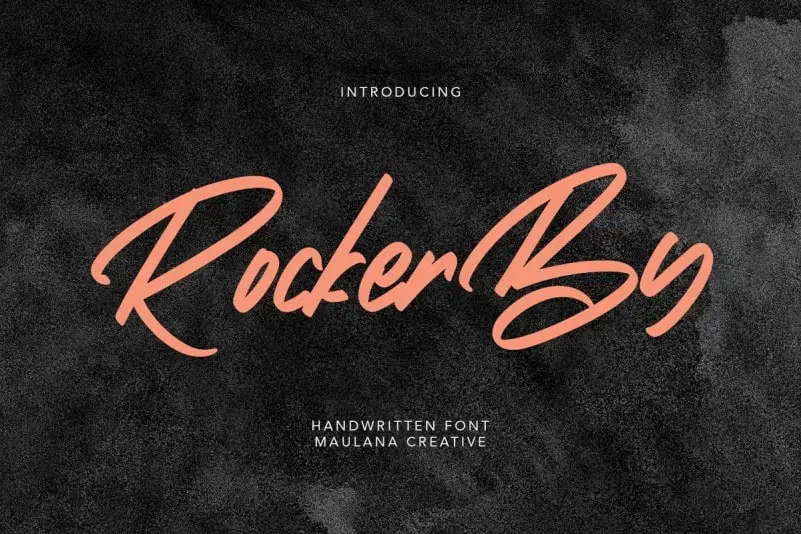
Rockerby Script Font – Download Grátis
Descubra uma nova fonte script gratuita para seu próximo projeto visual. Se você está procurando por uma fonte que possa dar um toque autêntico e único a suas criações, Rockerby Script Font é sua escolha perfeita. Dedicado ao designer Hamilton, essa fonte possui uma estética simples e elegante, perfeitamente adaptada para criar designs de assinatura, embalagens, materiais de impressão, identidades de marca ou até mesmo capas de livros. Rockerby Script é ideal não apenas por sua facilidade de uso e estilo moderno, mas também pela sua grande versatilidade. Com seu design cuidadosamente pensado, você pode experimentar diferentes maneiras de aplicá-la em seus projetos, como logotipos, tags publicitárias, capas de livros ou até mesmo rótulos. Além disso, Rockerby Script se destaca por ser uma excelente escolha para criar um visual atraente e profissional tanto no design editorial quanto na criação de sites e aplicativos. Essa fonte é perfeita para aqueles que desejam dar um toque único e autêntico aos seus projetos, garantindo ao mesmo tempo a qualidade e o conforto necessários para um trabalho bem executado. Seja você um designer profissional ou um amante do design, Rockerby Script pode transformar suas criações em verdadeiros objetos de destaque.